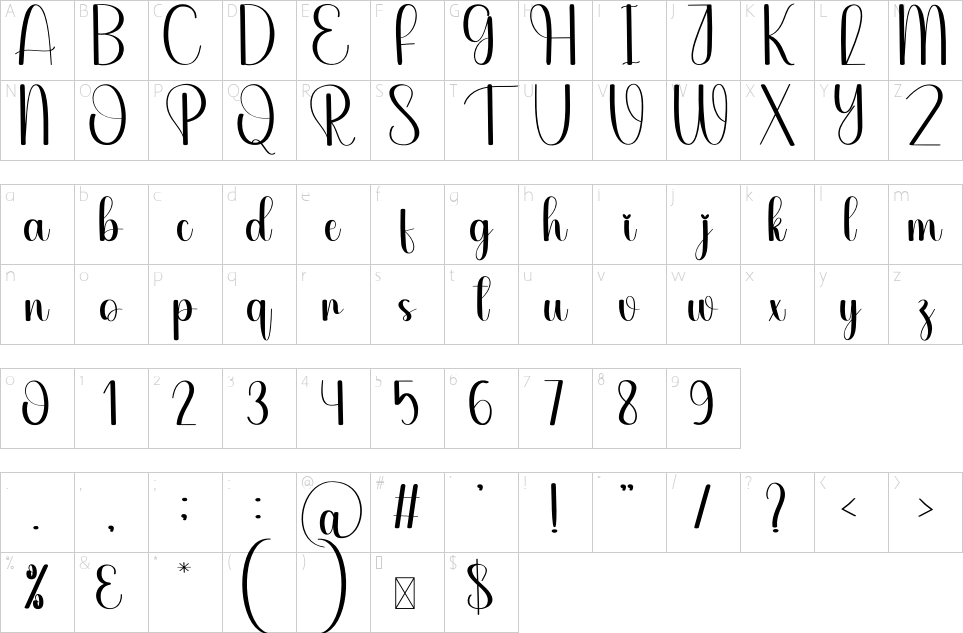
Descubra a atmosfera vibrante e natural da Atmosphere font, uma escolha ideal para criadores de design que desejam dar um toque único a seus trabalhos. Esta fonte foi cuidadosamente concebida por scratchones, disponível tanto para sistemas Windows quanto para Mac. Seus traços suaves e delicados criam um efeito visual leve e agradável, perfeito para gráficos, ilustrações e até mesmo para design de sites. Com sua designação de 395 downloads, a Atmosphere font é uma escolha sólida para aqueles que estão procurando por uma fonte de qualidade e estilo para seus projetos digitais. Descubra agora a atmosfera vibrante da Atmosphere font e dê vida à sua arte digital.